今回は、藤本健太郎著の『タイポさんぽ―路上の文字観察』をご紹介します。
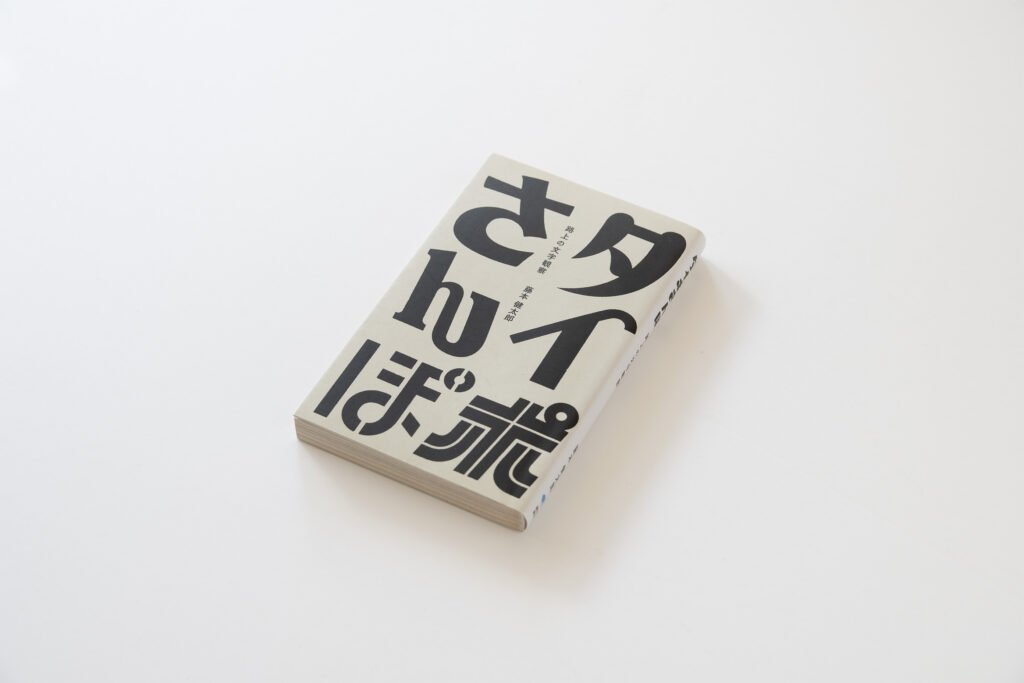
本書は著者が日本各地の路上で見つけた、看板や商品ロゴなどの文字たちとの出会いを記録したものです。自ら撮影した写真とグラフィックデザイナーである著者の視点から綴られた文章で120余りの事例が紹介されています。
本書で紹介されているのは、どれもアナログな手仕事の文字たちです。街の中で時代を経た姿は、現代のデジタルフォントでは再現することが難しい、深い味わいを醸し出しています。また、それらへの著者の考察が秀逸で、路上観察の面白さを知る良いきっかけになるのではないでしょうか。実際に私自身も路上でそのような文字を見つけると、ちょっとした有名人に出会ったかのような高揚感を感じてしまい、気づけば同じように写真を撮っていたことが多々あります。文字デザインに興味がある方だけでなく、どなたでも楽しめる散歩のお供にも最適な一冊だと思います。